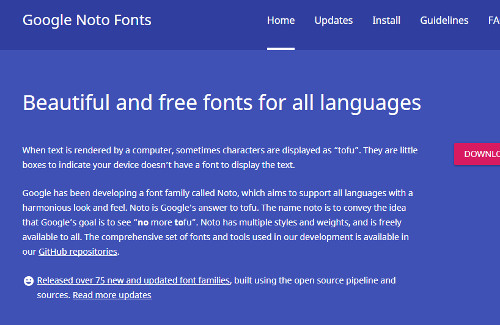
| 昨秋に出たfire10の第7世代。これがいい。キンドルはすぐ読めるし、バッテリー長持ちするし。なんといってもコスパ最強。でも、シンハラ語の利用者にはどうにもならない決定的な弱点がある。シンハラ語の文字が□□□□□□。豆腐表示されて読めない。もちろんメールも書けない。 |
FIREにもインド系文字がfireシリーズにもやっとインド系文字が加わったということを小耳に挟んだので、新しく出たfire10を仕入れました。タブレットのややこしい設定 はすべてアマゾンで引き受けてくれていますから、amazonから送られて来たfire端末に自分のwifi暗証番号を書き込むだけでネットへのアクセス はOK。 アマゾンがfireに用意してくれた絹ブラウザでネットに飛び込めます。絹ブラウザ検索エンジンのBeingで「スリランカ」を探して、さっそくスリランカ政府のホームページを開いて…っと。だけどここで、「ええっ」と引いてしまうはめに! スリランカ政府のトップ・ページが□□□□だらけ。見事に豆腐が並んでいます。目立つのはタミル文字。こちらはフリルのないきれいなフォントで表示されています。 タミル文字の上には□□□□。この豆腐の横並び、シンハラ文字の化け物です。ABCアルファベットもタミル語もfireタブレットにきれいに表示されたけどシンハラ文字が出てこない。豆腐化けしています。 シンハラ文字もユニコード化されているし、新しいパソコンには初期設定でインストールされているはず。これはおかしいと思ってfireのシステムの中の フォント・ファイルを覗けば、そこには有り余るフォント・メニューが並んでいるのに、あれ、シンハラ・フォントが見当たらない。 たとえば、インド系のフォントには、
NotoSansDevanagari NotoSansGujarati NotoSansKannada NotoSansKhmer NotoSansMyanmar NotoSansMalayalam NotoSansTamil NotoSansTeligu …などが収納されています。 フォント名のNotoはNo Tofu。これはNo more Tofu(豆腐文字はもう沢山)のこと。ネットからの豆腐文字撲滅を図るグーグルが高らかにNo more Tofuと謳ってアドベと共に開発した文字がNotoSans。 SansはSans serif、「フリルのない」という意味。余分な飾りは付けません。前世紀末に颯爽と登場したモリサワのDナール文字、当時は変体少女文字と言われたけど、あの柔らかい丸文字書体がSansに通じています。 fireのフォントファイルにこれだけ顔をそろえた豆腐撲滅系文字。だけど、fireのフォント・フォルダーにはシンハラ丸文字がない。 どうしたことだろうと訝ってグーグル・サイトを訪ねれば、NotoSansのフォントにはsinhalaも取り揃えてあることがわかります。いや、取り 揃えてあるどころか、NotoSansのSinhalaフォントは極細thinから極太blackまで、たっぷり36種あります。(参考 日本語フォントはNotoSansCJK JPとして7種です) ノー・モア・トーフ!ノー・モア・トーフ(豆腐はだめよ)のシンハラ・フォントをfire10にダウンロードしました。したにはしたのですが、これがfire10にインス トールできない。fire10の端末使用者にフォント・インストールの権限がないのが原因です。並みのandoroid端末ならスムーズにタブレット端末 使用者がsinhala fontを端末に組み込めるのですが、fire10は端末使用者によるシステムfontフォルダーへのアクセスを断固、拒絶します。fire10でシンハラ語が読みたい。そこで考えた。そうだ、アプリ・ストアへ行こう。 でも、amazonアプリ・ストアでシンハラ語関係のソフトを探したのは懸命な策じゃなかった。 amazonのandroidアプリストアには垂涎のシンハラ・アプリがいくつも並んでいます。このストアではgoogleストアより安全なアプリを扱っている。そんなうわさもあります。安心で安全。でも、なかなか噂どおりにはいかなかった。 amazonアプリ・ストアにPuvath Reader(「新聞早読み」)アプリがありました。fireにシンハラ語新聞を表示する無料アプリです。こいつはいける! でも、そもそもsinhala fontがfireのシステムにはないのでは? ないのならsinhala文字を表示できるはずがない。でも、このアプリを使うとシンハラ文字が表示されました。 そのわけは? これ、画像です。シンハラ語タイトルのお尻に張られたリンクから実際にシンハラ新聞のサイトへ飛ぶと見事なシンハラ豆腐の□□□□が列を成して天地左右に並びます。 このタイプのアプリの常ですが、インストールするとアクセス権限を行使してあなたのタブレットからあれこれ情報を取り出してどこかへ送ります。 でも、このソフトの場合、執拗さのレベルが低くて、広告勧誘やら課金サイトへの誘導といった悪魔の手練手管の汚れが今のところ小さい。 でも、ストアに並ぶそのほかのシンハラ語関連アプリには手ひどいのがあって、シンハラ語ソフトは動かなくても、広告を全面表示して、アクセス権限を断固行使するというものがあります。シンハラ音楽やシンハラ・ラジオ再生ソフトにありがちです。これは怖い。 昔、sinhala jokeboxというサイトがあってシンハラ音楽を縦横無尽に聞かせてくれたことを思いだして、「昔はよかった」などとローガイ感にふけってしまいました。 当たり前のことを当たり前にしたい現在、sinhala jokeboxにはアクセスできません。サイトがないようです。シンハラ音楽を聴くならyoutubeで再生するのが面倒に巻き込まれない穏便なやり方。そんな時代に落ちてしまったのか。アプリ・ストアを覗いたけどシンハラ語アプリはもう恐怖の対象。タジタジです。八九三のブタ・アプリです。シンハラ語学習がいやになってしまう。 このKhasyaReport「かしゃぐら通信」ではシンハラ文字をsinhala fontで表示する場面がサイトの中に多々あります。 現 在、KhasyaReportではスクール・ポタ(教科書体)unicode とkapruka社固有の古いsinhala fontを使用しています。kapruka謹製のsinhala fontはunicodeが生まれる前のものでキーボード打ち込みが直感的にできて、便利、重宝して使っていました。でも、時代はユニコード。これは順次 unicodeにリフォーム中です。リフォーム前のものはkaputa fontを持っていないと豆腐状態になります。 しかし、fireタブレットにも穴がある。グーグル翻訳の驚きこうまでしてシンハラ・フォントを遠ざけるamazon fireなのですが、amazonnさんはちゃんと抜け道を用意してくれています。それは「グーグル翻訳」をfireで使うと、ちゃんとシンハラ・ユニコード・フォントを表示してくれるのです。だから、グーグル翻訳を開いて「日本語→シンハラ語」転換をすれば、皆さんがシンハラ語の話し方でお読みになるシンハラ・フォントの形でシンハラ語が表示されます。初期のグーグル翻訳と違って、このところ、翻訳の精度は良くなっています。もともと、シンハラ語のユニコード化と英語への機械翻訳はグーグルがスリランカ政府に関わる形で始まりました。シンハラ文法の解析をシンハラ語の助詞であるニパータnipataに焦点を当てたのもグーグルによるシンハラ語の機械翻訳に立ち向かったグーグルの功績です。 さて、なぜ、グーグルはライバルのアマゾンの専売タブレットの中でシンハラ語を自在に操れるのか、これは、私にはさっぱり分かりません。アマゾンが鎖国をやめたという噂を耳にもしますが、はて、はて。 残念ですがfireタブレットではKhasyaReportのシンハラ語文字はすべて□□□□の豆腐表示です。当サイトはシンハラ・フォントを使用していますので、トウフ文字のお困りの場合、ほかの社のタブレットでご覧になるか、PCのご利用をお勧めせざるを得ません。 fireシリーズ。amazonファンとしては使い勝手がいいし、何よりコスパが最高で手放すことは考えたくもない。 シンハラ文字を読む。その当たり前のことを当たり前にしたい。ノゥ・モア・トーフ! シンハラ・フォントが装備される次世代、次々世代fireの登場を期待します。 |